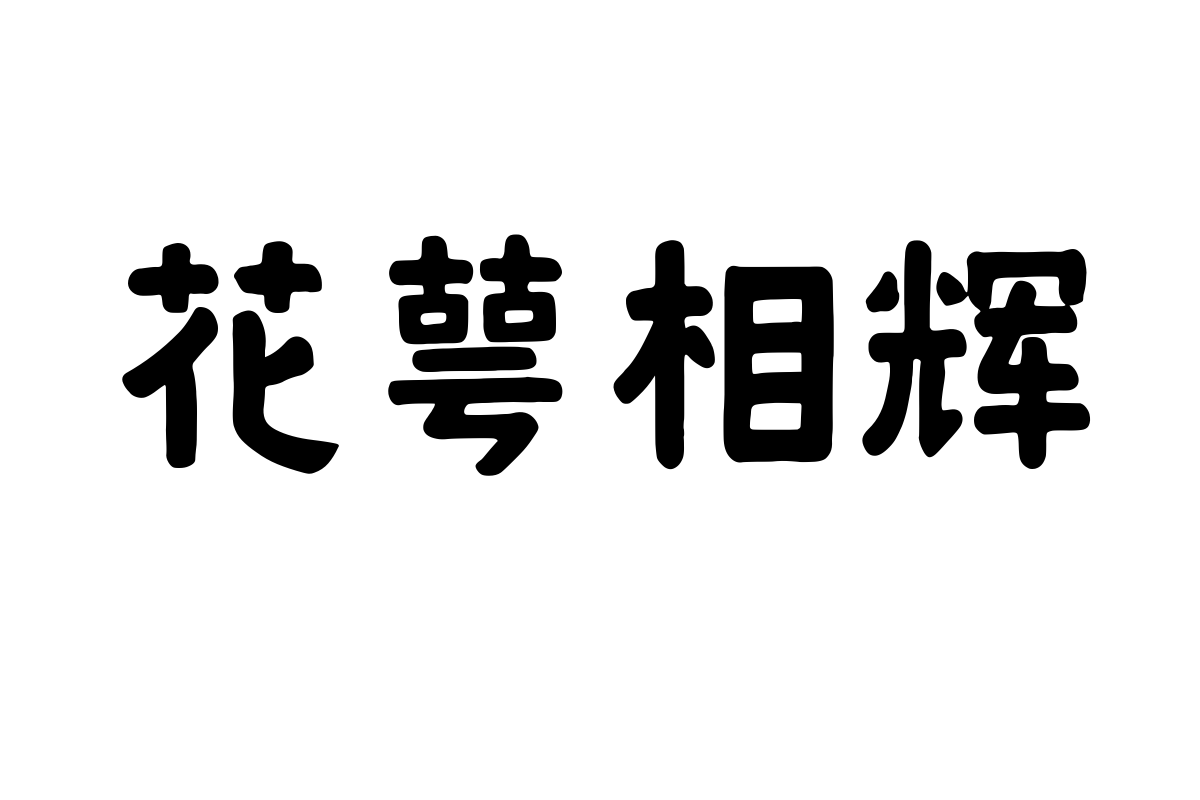
也字工厂清补凉体是一款具有独特风格的字体,其特点如下:
1. 字形结构:该字体的字形结构简洁明了,笔画流畅自然,给人一种清爽的感觉。每个字的笔画都经过精心设计,使得整体字形更加和谐统一。
2. 字体风格:也字工厂清补凉体采用了现代简约的风格,没有过多的装饰和繁复的设计,给人一种清新脱俗的感觉。这使得字体在视觉上更加简洁明快,易于阅读和识别。
3. 应用场景:该字体适用于需要展现清新、简约风格的设计场景,如广告、海报、网页等。它能够很好地融入各种设计风格中,为设计作品增添一抹亮丽的色彩。
总之,也字工厂清补凉体是一款具有独特风格的字体,适合用于需要展现清新、简约风格的设计场景。它的字形结构简洁明了,笔画流畅自然,能够为设计作品增添一抹亮丽的色彩。